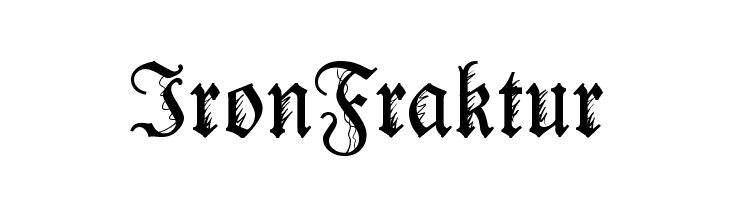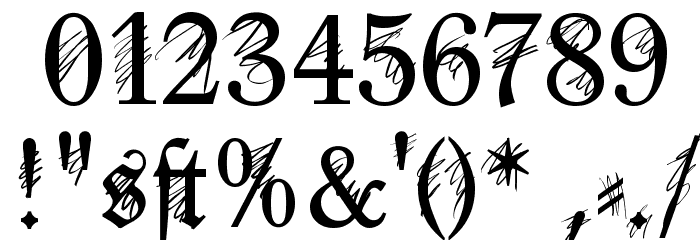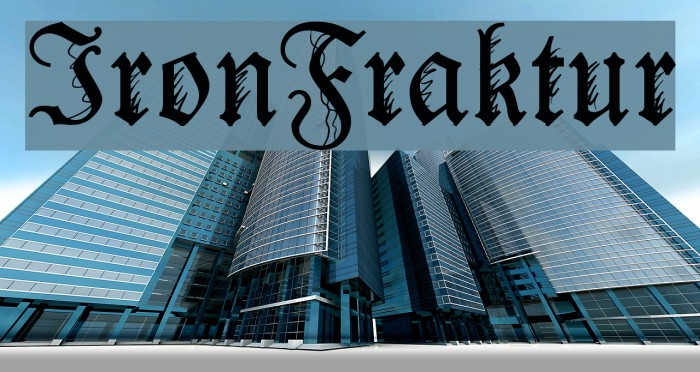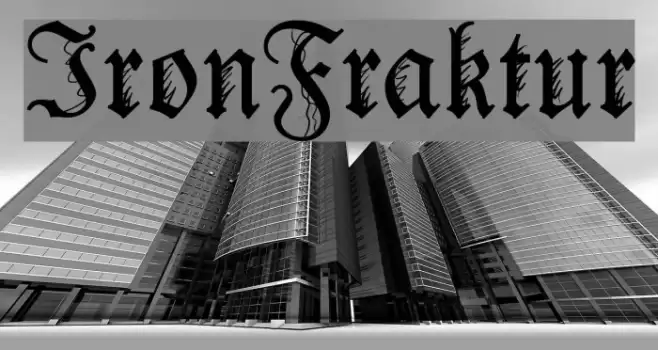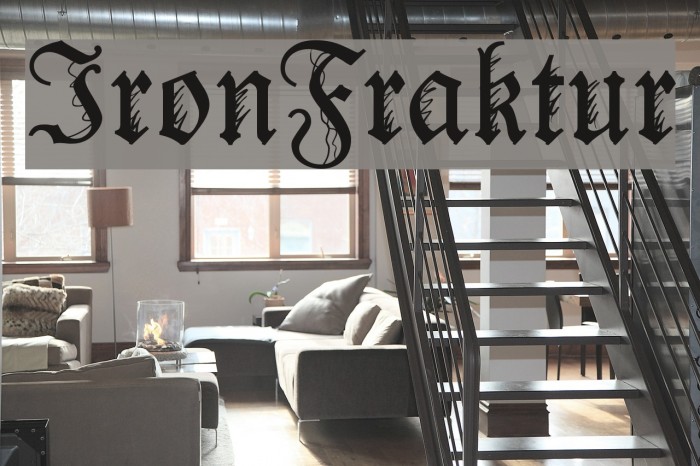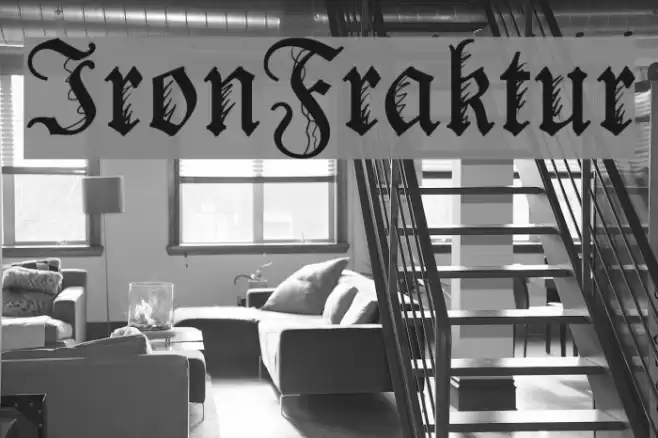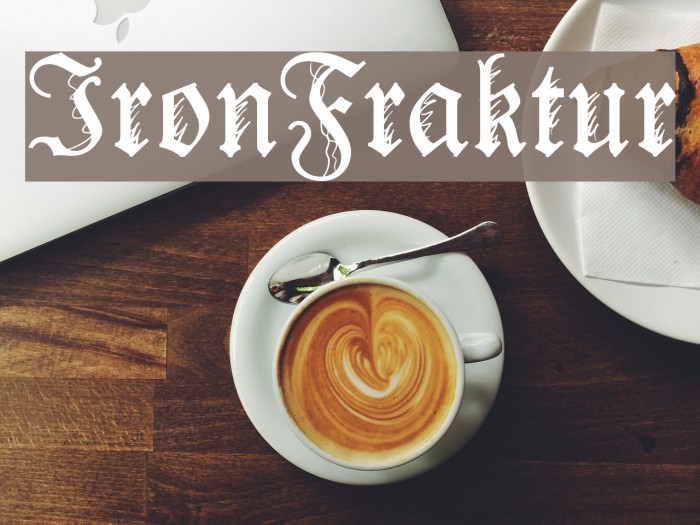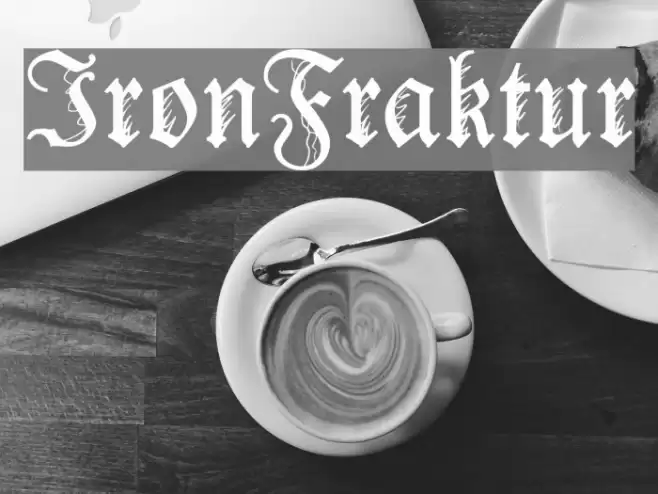
IronFraktur Font
| Kategorien | Calligraphic |
| Gesamtstil | Vintage |
| Anwendungsfall | Logos, Headlines, Decorative text |
| Vorgeschlagene Projekte | Ideal for historical documents, wedding invitations, book covers, and branding that requires a classic or medieval touch. |